1、简约时尚类
这一类是无衬线体 (Sans serif)系列,线条柔美,造型自然流畅,用在海报、详情页简直完美!
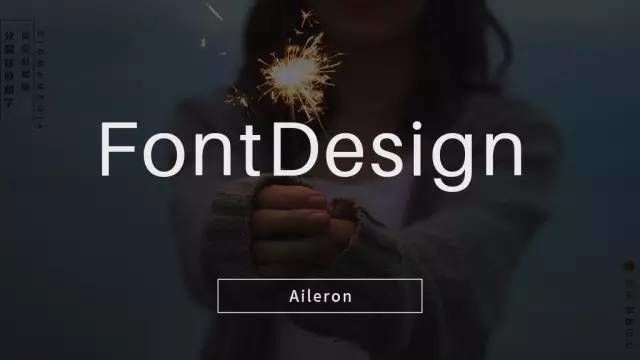
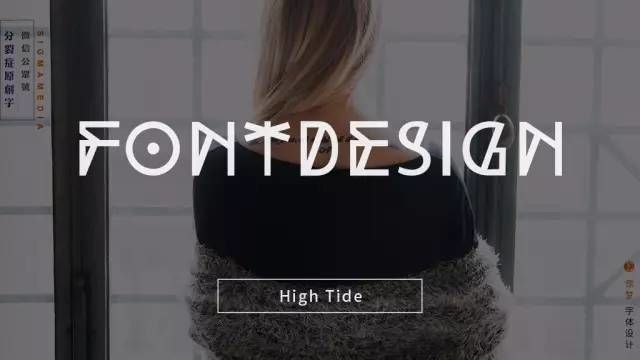
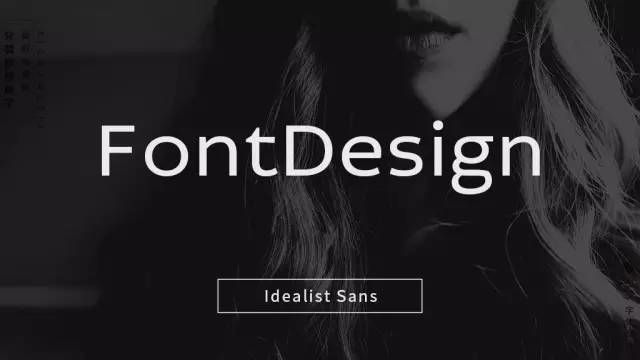
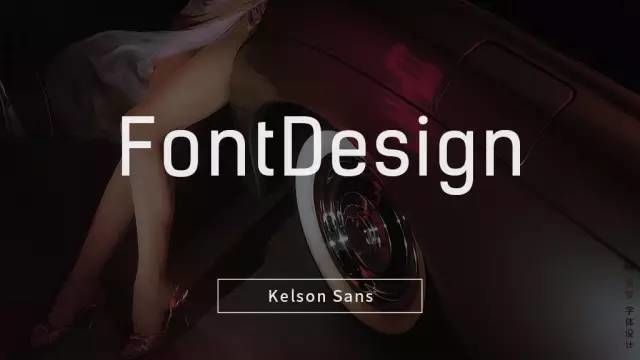
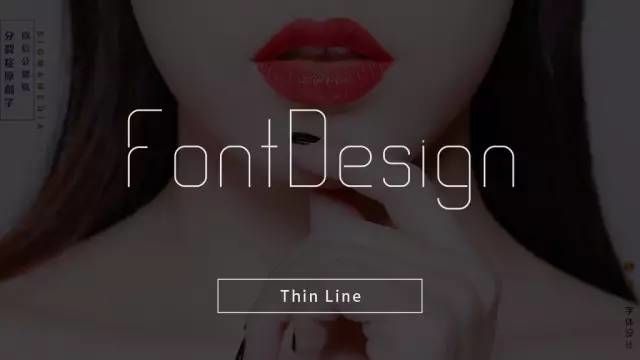
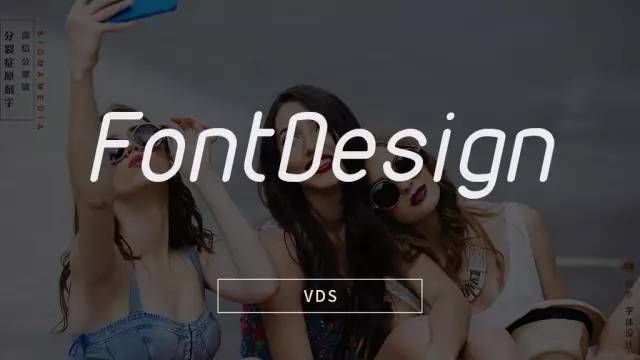
2、浑厚吸睛类
有灯光的地方就是舞台,而有这类字体的地方就是焦点!这类字笔画较粗,浑厚有力,很适合用作标题或口号,醒目吸睛自带BGM。
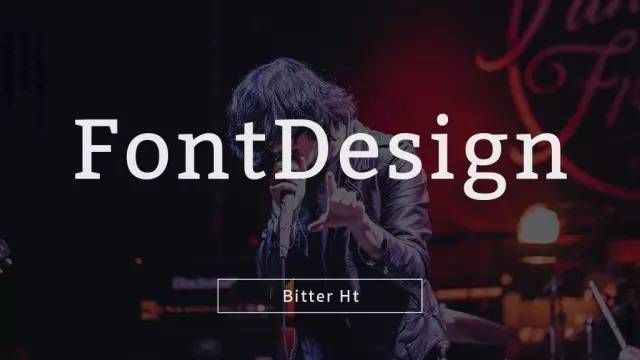
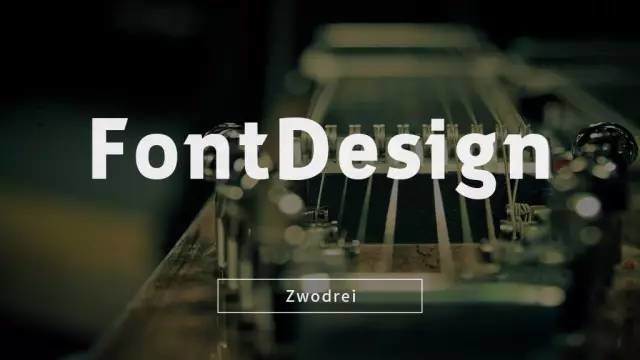
3、锐利俊朗类
自在如风的少年锋芒毕露,那这类字再适合不过了,衬线字体(Serif)起落有装饰,总有一种考究和修饰过的美,一如你总是洗头换装后给人的感觉。
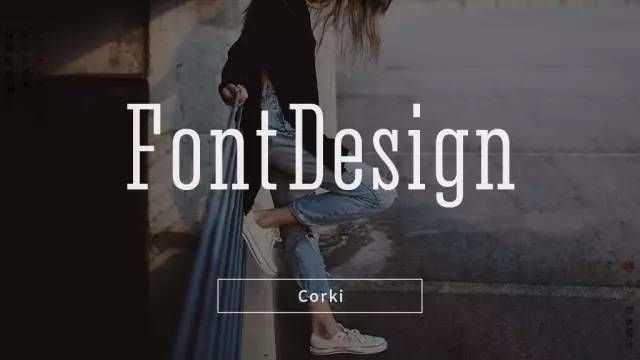
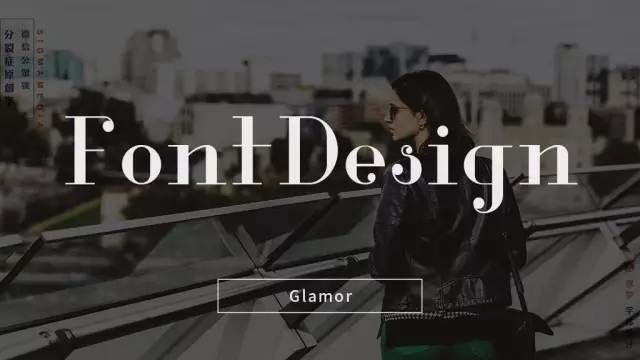
4、随性手写类
怀念懵懂之际书写出的阿波次德?也许从手写英文中能寻得那些年的一丝洒脱与不羁的赶脚,随性手写但更艺术化,可以可以。
5、个性放飞类
人不轻狂枉少年,谁还没点个性咋滴?这类字或笔画出众或造型奇特,就是不安常规出牌,总能在特立独行中俘获你的心。
6、狂野复古类
就知道你有一颗躁动不安的心!干净整洁给人清爽的美,而污渍飞溅给人复古的美,该类字的特点就在于满足异样的品味,相信能让处女座抓狂。
7、图案装饰类
用字体代替图形成为视觉焦点是平面构成中常用的手法,而这类字绝对当之无愧可以撑起整个江山!该类字可以说是抢别人饭碗的存在了。